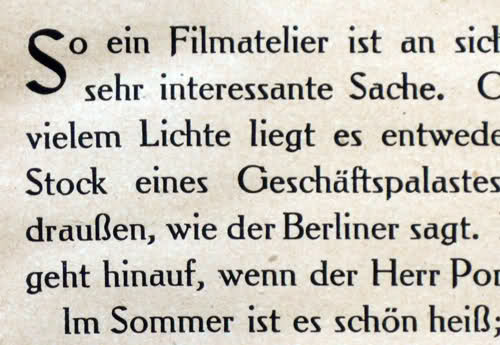
schrullige Brotschrift
Hallo, kennt jemand diese bemerkenswerte Type?
klarer fall für pachulke, würd ich sagen.
(ich hab gerade keine zeit mein schriftmusterbuch der stempel ag von 1918 durchzuackern)